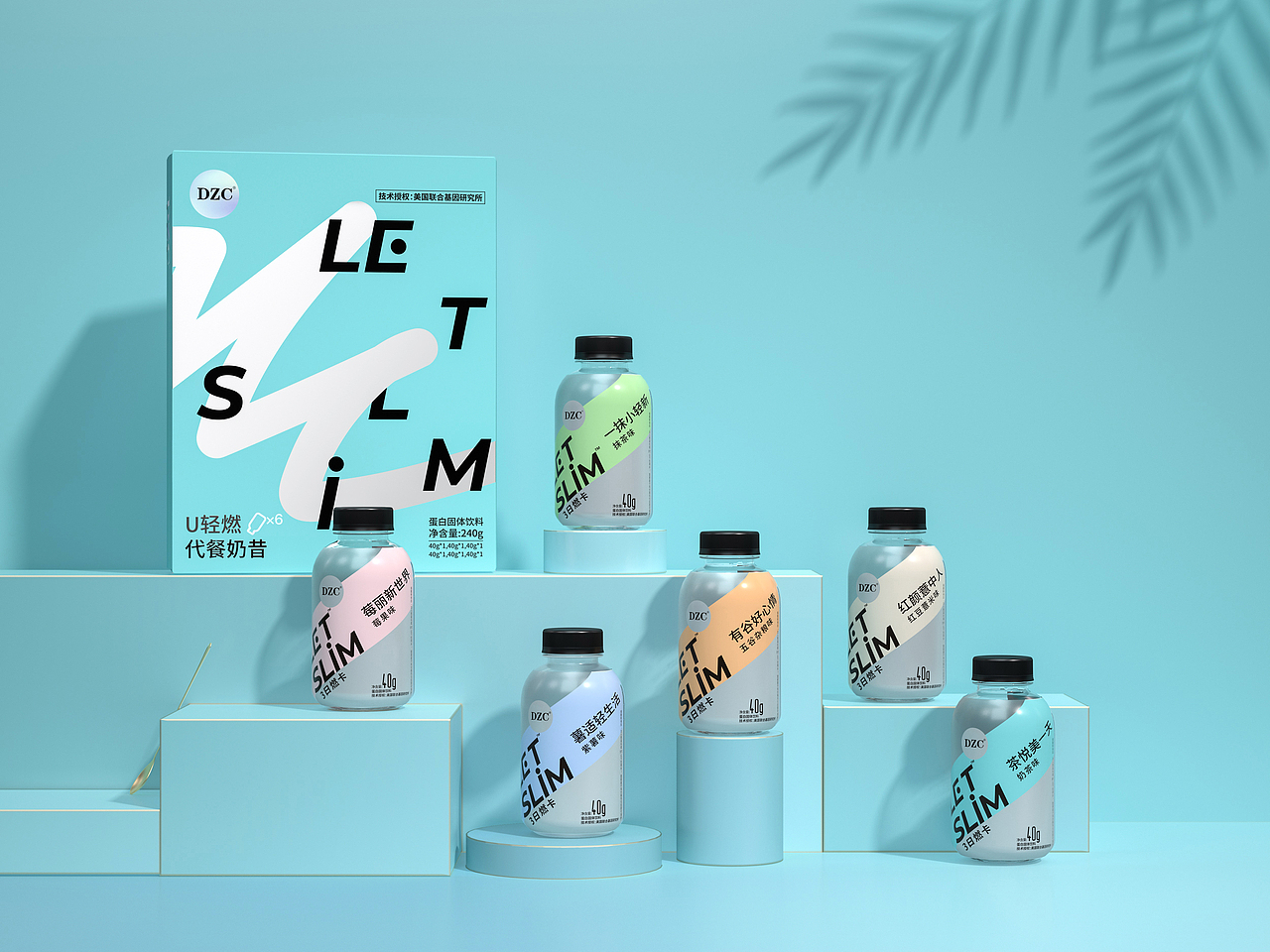
DZC | 高端代餐固体饮料瓶贴平面包装设计
DZC
U轻燃代餐奶昔
DZC品牌一直倡导“内调外养完美结合”的产品理念,秉承越分享,越美丽的品牌理念,致力于帮助女性解决内在健康与外在美丽问题,让万千女性由内而外绽放自然之美。Hellolink品牌包装设计实验室为其设计的包装风格符合品牌的高端性和年轻化的需求,具有女性时尚感。
颜色方面,选用了蒂芙尼蓝绿色作为底色,提升了包装整体的时尚潮流感。采用蓝粉色对比色进行撞色的色彩搭配,粗线的英文字体交错排布,对比更加强烈。
包装使用烫银、uv起凸工艺,以此提升包装整体反光度,加强质感,提高整体的层次性,也进一步加强包装质感,利用英文增强高端性与国际感。
瓶子包装利用色块相辅相成形成了出色的对比,交相辉映,传递出DZC品牌产品的文化内涵,给人以强烈的视觉代入感。排版上运用侧式排版,打破了传统居中对齐的局限性,设计感更加独特灵动,整体包装时尚简约,版式新颖,简洁不失大气,外盒和瓶子上做镭射及漏空工艺,增加产品温度。